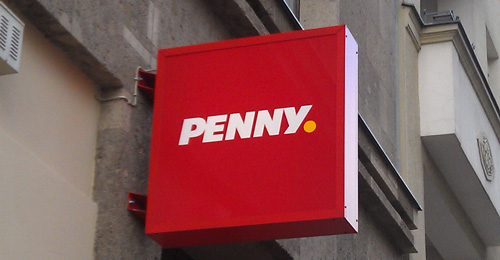
Wie der stets gut unterrichtete Supermarktblog heute verkündet, hat in einigen Berliner Filialen der Rewe-Tochter Penny der »Umbauschlussverkauf« begonnen. Damit nicht genug: Die ersten neuen Transparente hängen schon an den Fassaden. »Wir verändern uns. Frischer. Besser. Überraschend«, verspricht Penny seinen Kunden auf Plakaten, die der Kundschaft den Imagewandel vermitteln … denn sie muss für eine Woche draußen bleiben.
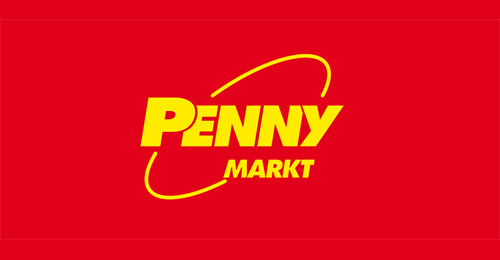
Laut »Lebensmittelzeitung« sollen 2012 rund 800 Märkte in Deutschland neu gestaltet werden, was mit 150 Mio. Euro zu Buche schlagen wird. »Die radikalen Änderungen sind ein mutiger Schritt« schreibt der Supermarktblogger Peer Schader, denn das neue Design sei Welten entfernt »von den Bruchbuden, in denen Penny bisher seine Waren verkauft hat«. Vor allem aber schlage Penny eine völlig andere Richtung ein als die direkte Konkurrenz. Die Läden von Lidl seien zwar in Ordnung, aber kein Design-Highlights; Netto kämpfe immer noch mit der Integration der Plus-Filialen und den übrig gebliebenen orangefarbenen Kassen, »die sich fies mit den eigenen Logofarben gelb und rot beißen«; und Aldi se komplett auf Zweckmäßigkeit eingestellt.
Das neue, kontrastreiche Penny-Logo lehnt sich ang an dem der Mutter Rewe an: weiß auf rotem Grund. Das Gelb ist fast komplett verschwunden, nur der Punkt hinter dem Markennamen trägt noch die Farbe und erinnert ein bisschen an den Namensgeber, den Pfennig. Die Versalbuchstaben P und Y überlappen sich nicht mehr mit ihren Nachbarn, aber sie berühren sich noch – was nicht sein müsste und der Wortmarke eine zweifelhafte Eigenständigkeit verleiht. Überhaupt scheint die Spationierung das Hauptproblem des Logos.
War das eine Spontan-Aktion? Unser PENNY hier ist mit einem Neubau erst fertig geworden, trägt aber noch überall riesengroß das alte Logo. Wahrscheinlich gab es ein Stichtag, ab wann das neue Logo im Einsatz ist. Und wohl besser als gar kein Logo auf dem Haus :-)
@Ben: Schauen Sie mal am Eingang auf das Schild mit den Öffnungszeiten. Da müsste das neue Logo schon klein in der Ecke stehen, auch bei Märkten, wo sonst das alte Logo noch hängt. (Gilt aber nur für die Märkte, die bereits im neuen Design umgebaut sind.)
Besser ohne Frage. Aber bin ich hier der Einzige, der am PE hängen bleibt?
Wir gehen zwar oft bei Penny einkaufen, aber sehe bisher immer das alte Logo?
@R::bert: Nein, bist du nicht der Einzige. Etwas unentschlossen und wage, auch bei N und Y. Fängt an zu flimmern, wenn man zu lange hinguckt.
Da bin ich aber beruhigt Franzi …
Wahrscheinlich sollte es eine Art Redesign werden, welches Anleihen vom Alten rüberrettet. Wohl keine so gute Idee …
ist die neue schrift bekannt .?